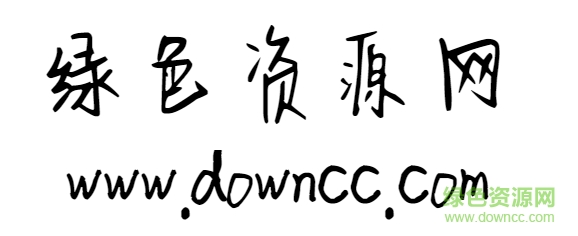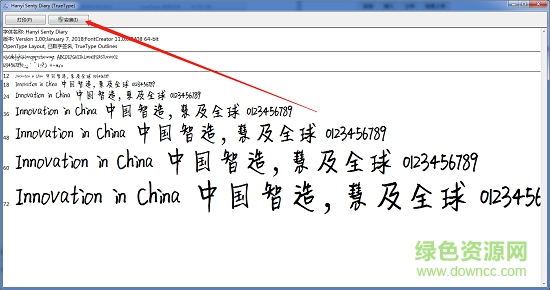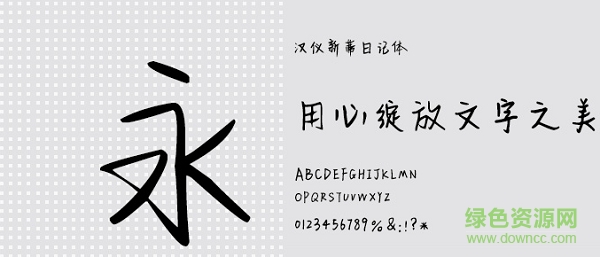
漢儀新蒂日記體是一款非常飄逸的漢儀字體,簡(jiǎn)單隨意的筆鋒讓字體看起來(lái)更加的簡(jiǎn)單隨意,用戶可以使用于多個(gè)不同的地方,簡(jiǎn)單又富有特色,喜歡就來(lái)綠色資源網(wǎng)下載吧!
漢儀新蒂日記體是漢儀字庫(kù)開發(fā)的一款利落、簡(jiǎn)明的鋼筆手寫字體,該字體以硬筆書寫,依舊體現(xiàn)了漢字筆勢(shì)的微妙變化,整體效果非常出色,用戶可將字體使用多個(gè)不同的作品的排版設(shè)計(jì)等等,優(yōu)雅大氣!